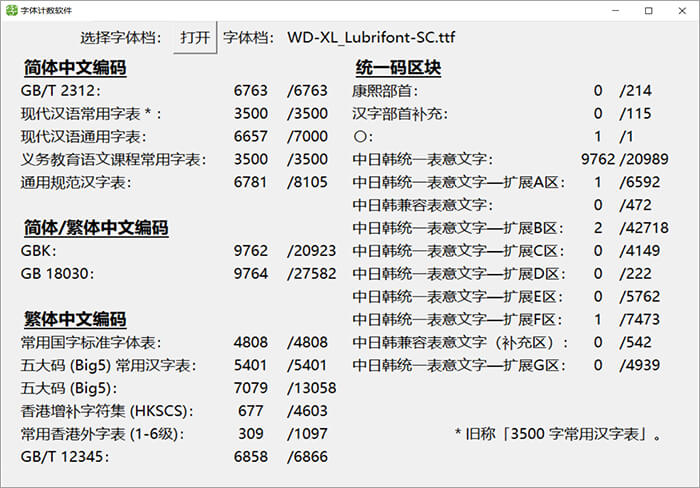
WD-XL滑油字是在站酷庆科黄油体的基础上为繁体(正体)中文进行补字扩充,让其能够适配繁体(正体)中文环境,并且也补全标准中文字体所需的标点符号和功能。WD-XL滑油字修正了站酷庆科黄油体一些原有字体的BUG,并且对部分字型进行了优化。
WD-XL滑油字增加了OpenType 功能 features,如需了解功能的详情,可以点击这里进行查看。
所有的“飠”都少个点,“蝕”字更是写成了“食虫”。
TC版若要做传承字形,“飠”为何不写为“?”?
关于“飠”旁,基本上没有修改原字体,考虑原因是因为涵盖的字符数量太多了;TC版未修改“飠”为“?”的原因同上。少的点没有补上是因为左上角已经太黑了,除非把“人”的笔画弄细,否则只会显示成一个黑色三角形。另外本字体并不是作为内文使用的字体,因此经考虑后才做出以上决定。
“蝕”字属于原字体的bug,您可以在GitHub上开启新issue,下版本将会修复。
发完了,发现并修改了5个字:茛蝕谡亂覜
如果改的不好的话帮忙再细化一下。
原版的作者因為繁體好難,把「譏」的右邊寫錯成「歲」了,結果出現了不常用的字。
嗯,顺便把错字移去正确码位了 ?
那個「起」的己怎麼沒變成巳?
(忘了?)下一版会改进,当然如果需要欢迎去GitHub开一个新issue
本字体是使用 Google Fonts 开源版本,该字体对比站酷版本其实少了大量字符(看回站酷版就会发现emmm…),使用的版本 GitHub 在此:https://github.com/googlefonts/zcool-qingke-huangyou